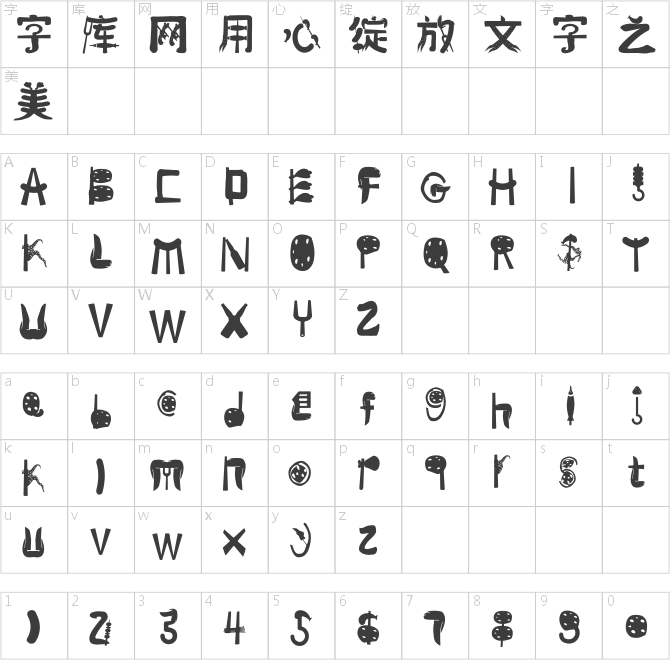
字体名称: 逐浪海鲜排档撸
逐浪海鲜排档撸串体
一款拟物的汉字,因为烧烤夜宵店老板要求而产生这个创意,尽量的拟物,按gb2312规则编码,特别适合海鲜店、排档、烤串店使用。
1、因而为烧烤、撸串字体,所以处理过程中可增加一些“咬痕”如丁字一横。有如三五好友一同撸串,更为真实。
2、本案大多偏旁都以烧烤串外形演变而来。
3、烈字,加上少许“热气”外观,犹如刚出炉的烤串,显得更为真实。
撸字,右边的田字左上角,有一张嘴巴,拟人化形象非常逼真。
民以为食为天,食以味为先。
一款以夜宵撸串为主题的字体,其精髓在于如何应用场景以及拟物的真实,并不失去可识别性,这需要研发与设计团队付出极大的心血。
为此,逐浪字库人,考量了多种场合以及识别距离,引入了unicode 13标准,进行了矢量化的识别,支持高清展示。
整个字库,不仅是汉字,英文、标点符号以及横竖排版,均进行了专业的精良设计与生产,支持严谨的国标产品线。
整个字库的生产历晚一年,先后考察了13个省份(自治区)以及港台地区餐饮应用场景,进行了多场景识别与试验,最后成型,具备良好的应用与扩展功能,提供矢量化样本与全库应用,工艺精良,风格特别,原创与开拓并举,引领中国与华文字库产业进入全新拟物时代。